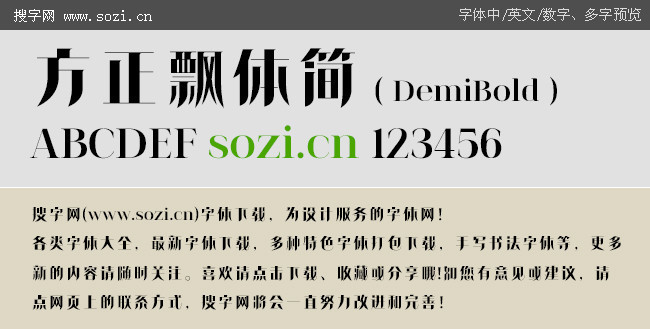
方正飄體簡(jiǎn)DemiBold
搜字網(wǎng)提供一款方正飄體簡(jiǎn)中文字體下載,方正飄體系列字取柔美之姿,飄逸之感,適合于追求優(yōu)雅品格類別的相關(guān)標(biāo)題。于字里行間,求風(fēng)度之翩翩,展高挑之身姿,顯優(yōu)雅之品行,有微風(fēng)緩緩吹來(lái)之感。由粗至纖細(xì)五款系列,粗體穩(wěn)重而醒目,細(xì)體別致而性感,總之體態(tài)各異。適合應(yīng)用于藝術(shù)設(shè)計(jì)、平面宣傳設(shè)計(jì)、網(wǎng)頁(yè)設(shè)計(jì)等場(chǎng)合使用。